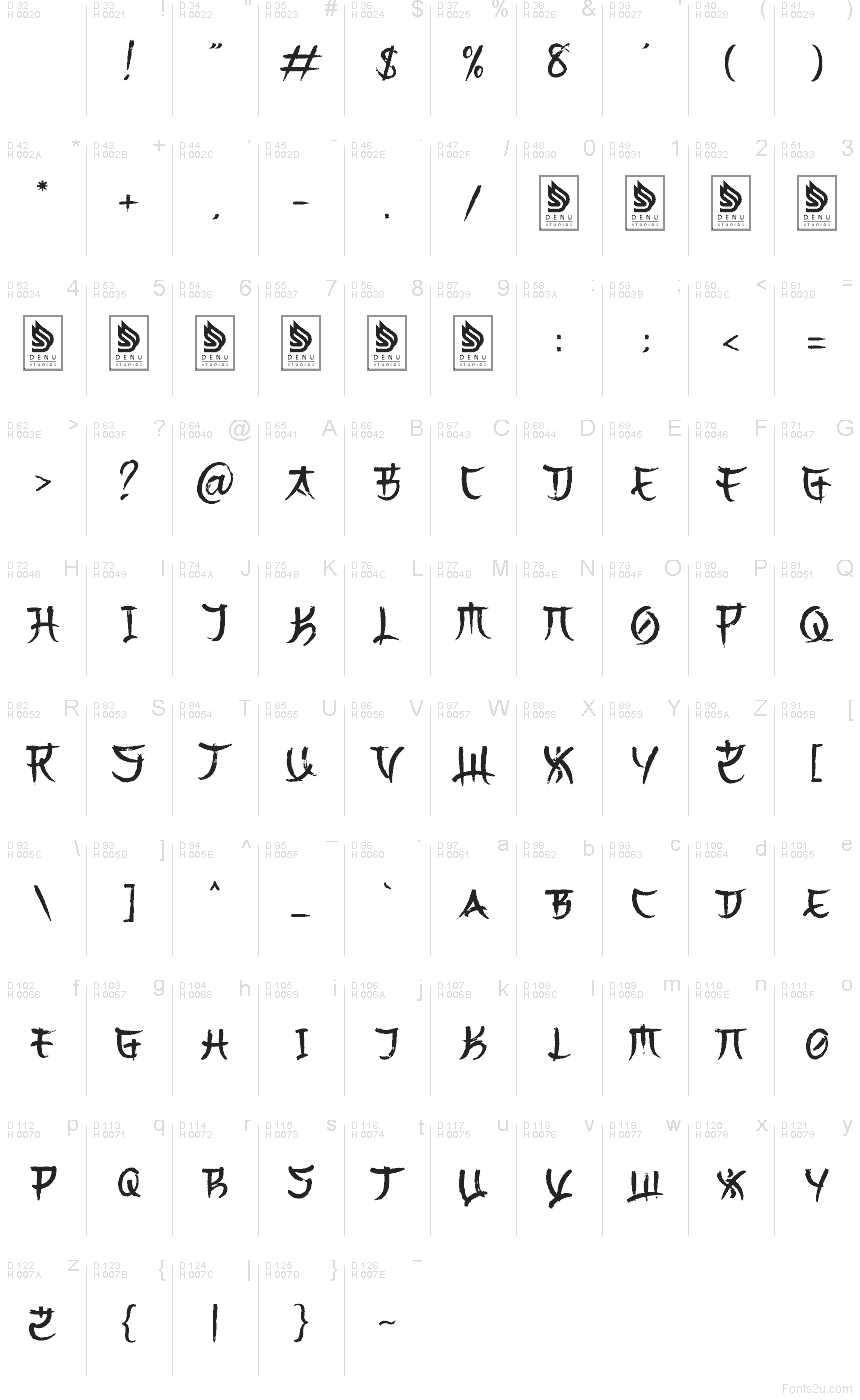
Yoru Kaze od Denustudios je bezplatné japonské písmo s drsným rytmem tahů štětcem. Písmena působí svižně a větrně, s typickými přerušeními suchého štětce, zužujícími se tahy a mírně nepravidelnými křivkami, které dodávají celému designu ručně vyráběný vzhled namísto pouhé dekorace.
Hodí se na plakáty, branding ramen bister, hudební obaly, titulky a obaly produktů, které vyžadují přímý kaligrafický úder. Jako bezplatné písmo je Yoru Kaze obzvláště užitečné pro krátké nadpisy, loga a výrazné editační prvky, kde drsné okraje štětce a rychlé tahy odvedou většinu práce.